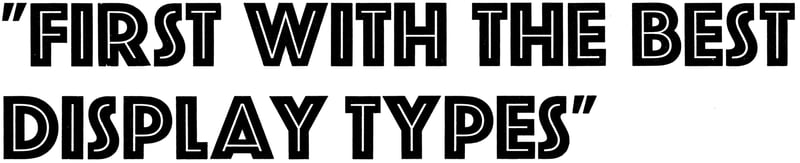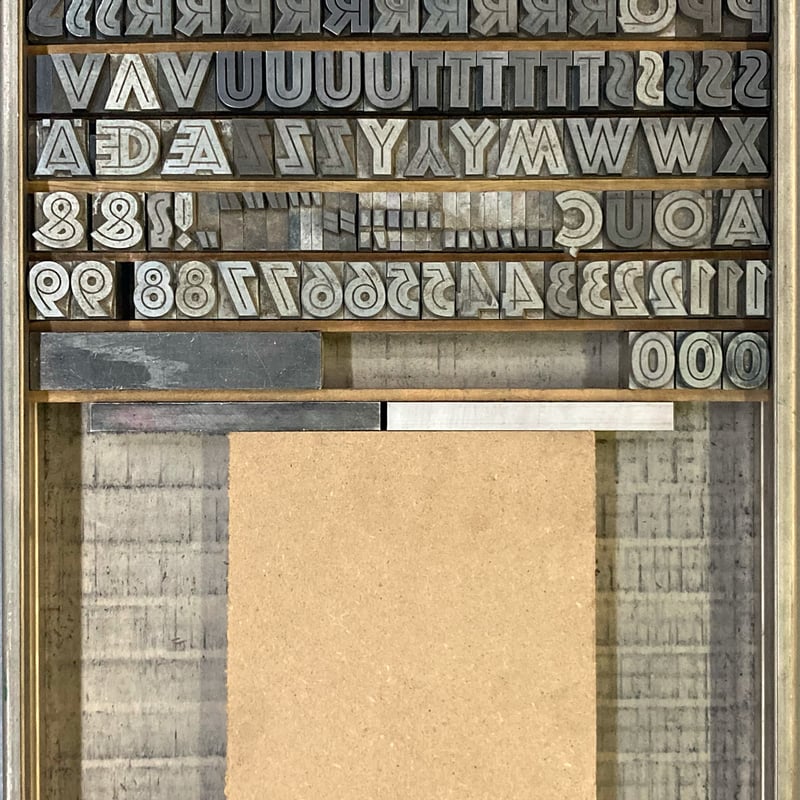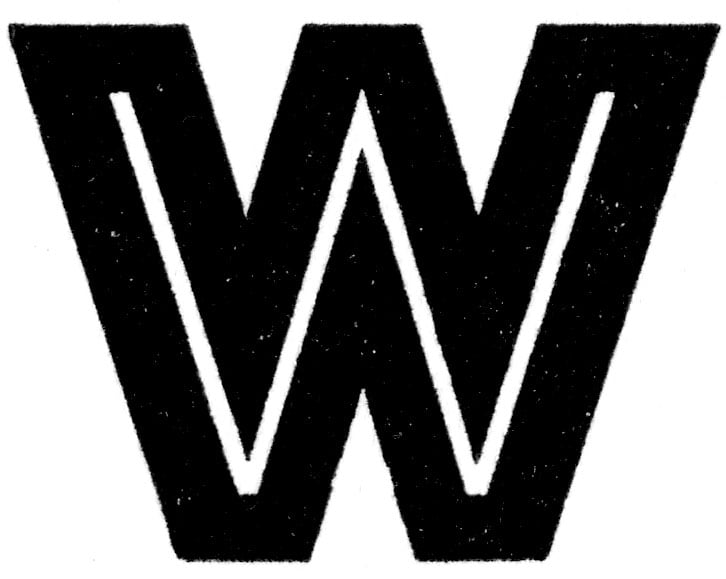
Phosphor
Druckmuster mit Text «Lichte Fette Grotesk / Phosphor, 48pt»
Klassifizierung
Display
Design
Jakob Erbar
Jahr
1923
Schriftgiesserei
Ludwig & Mayer
War als Lichte Fette Grotesk Teil der Erbar-Grotesk Familie, wurde aber unter verschiedensten Namen gehandelt, im Ausland als Phosphor, siehe Fonts in Use. Rechtwinklig geschnittene Varianten von K, R und Y, Varianten auf schmalem Kegel von A, T, V, W und Y, sowie ein alternatives S.